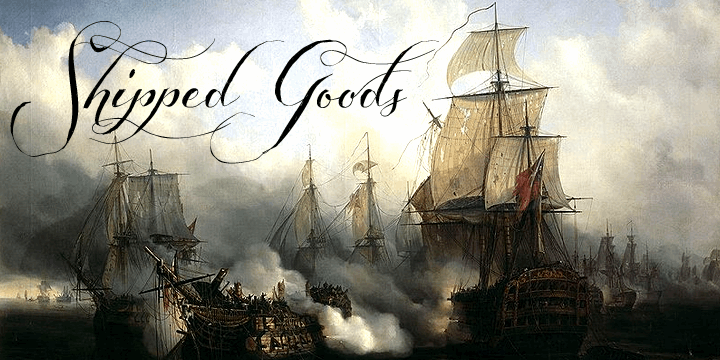
Shipped Goods font
A fonte Shaved Goods é uma escolha perfeita para designers que buscam um script fluido e elegante. Hamilton, o criador desta fonte única, trouxe consigo uma paleta de personalidade e estilo que torna qualquer projeto uma experiência visual fascinante. Se você está procurando por uma fonte do tipo script que pode se adaptar a um amplo espectro de projetos, Shaved Goods é definitivamente sua escolha. Suas letras fluidas e delicadas criam um toque sofisticado em designs gráficos variados, desde cartazes publicitários até websites elegantes. Para quem está pensando em incorporar esta fonte à sua estratégia comercial, Hamilton disponibilizou a opção de adquirir uma licença comum. Visite o site fornecido na descrição original para explorar todas as possibilidades e fazer um investimento lucrativo no seu próximo projeto. Shaved Goods é mais do que simplesmente uma fonte – ela é uma paleta que adiciona movimento e personalidade a qualquer design, transformando os textos em algo realmente único e memorável.